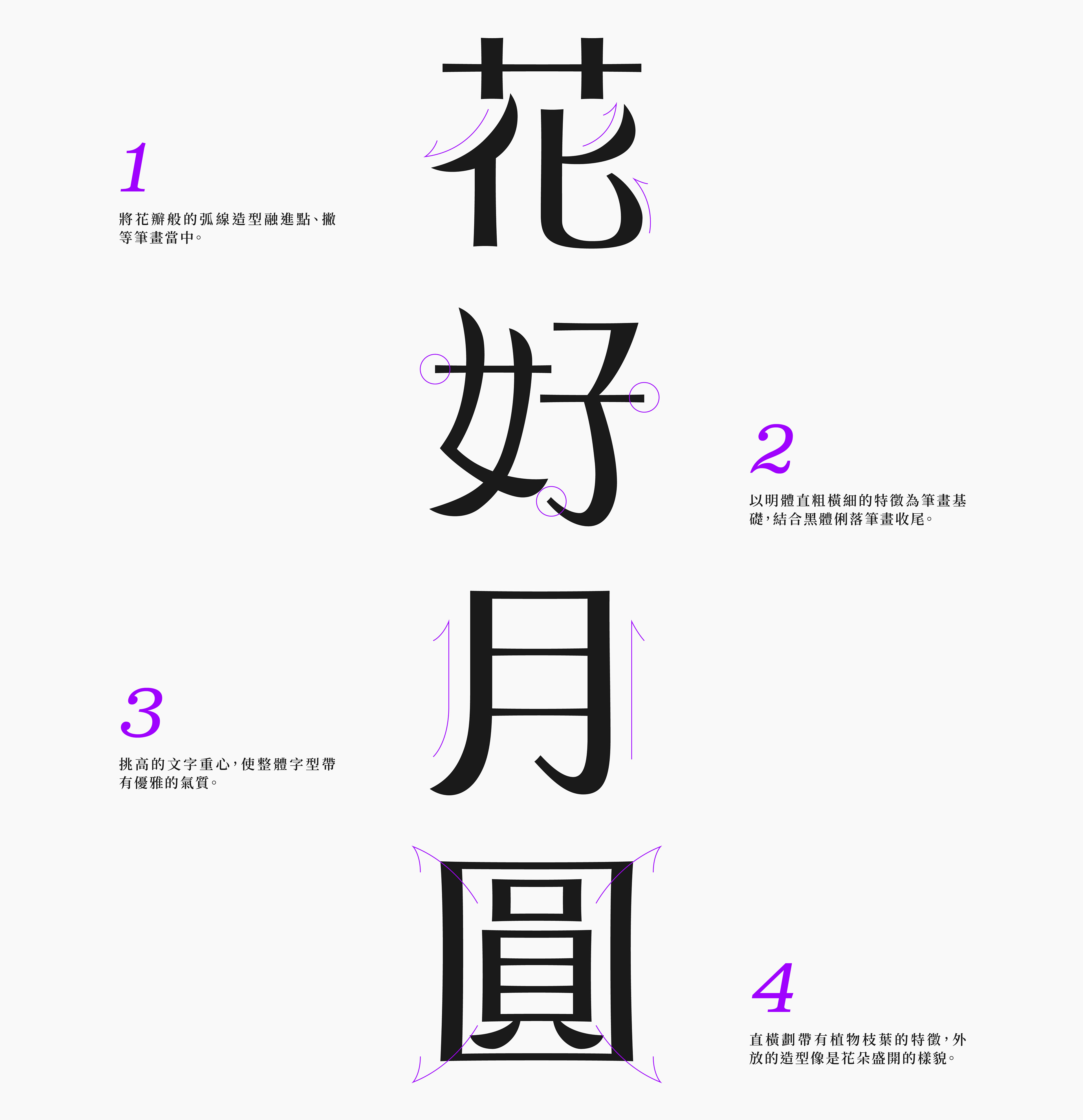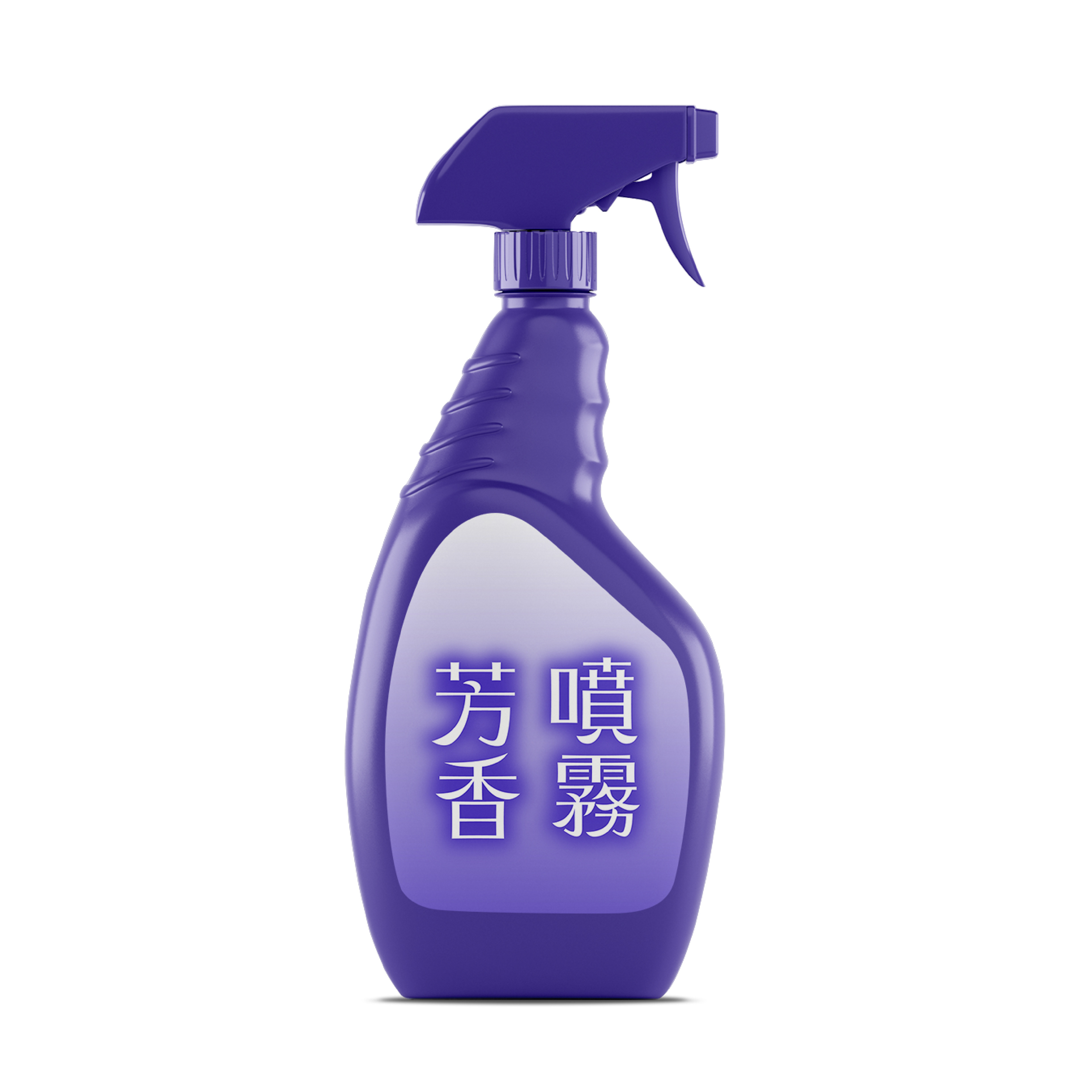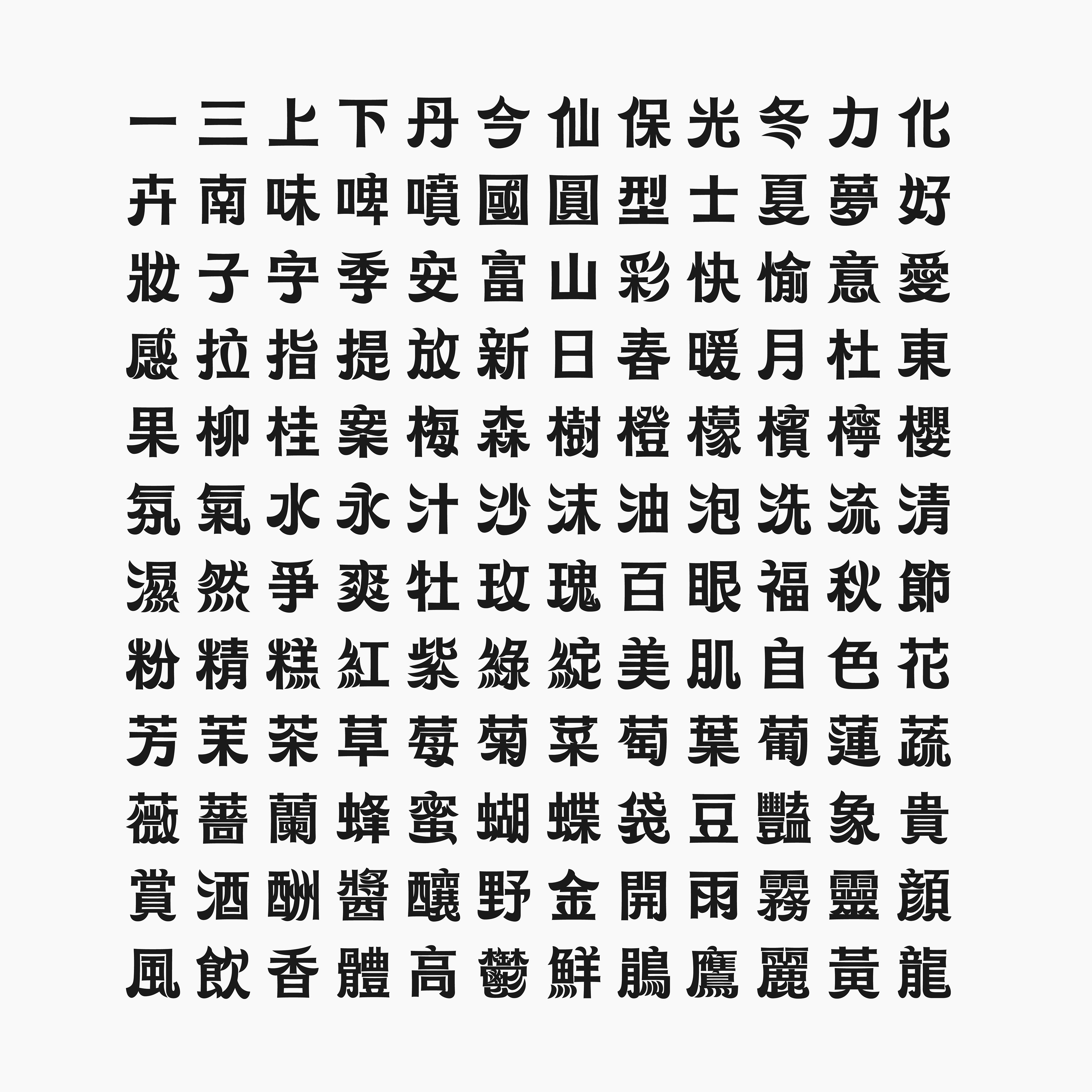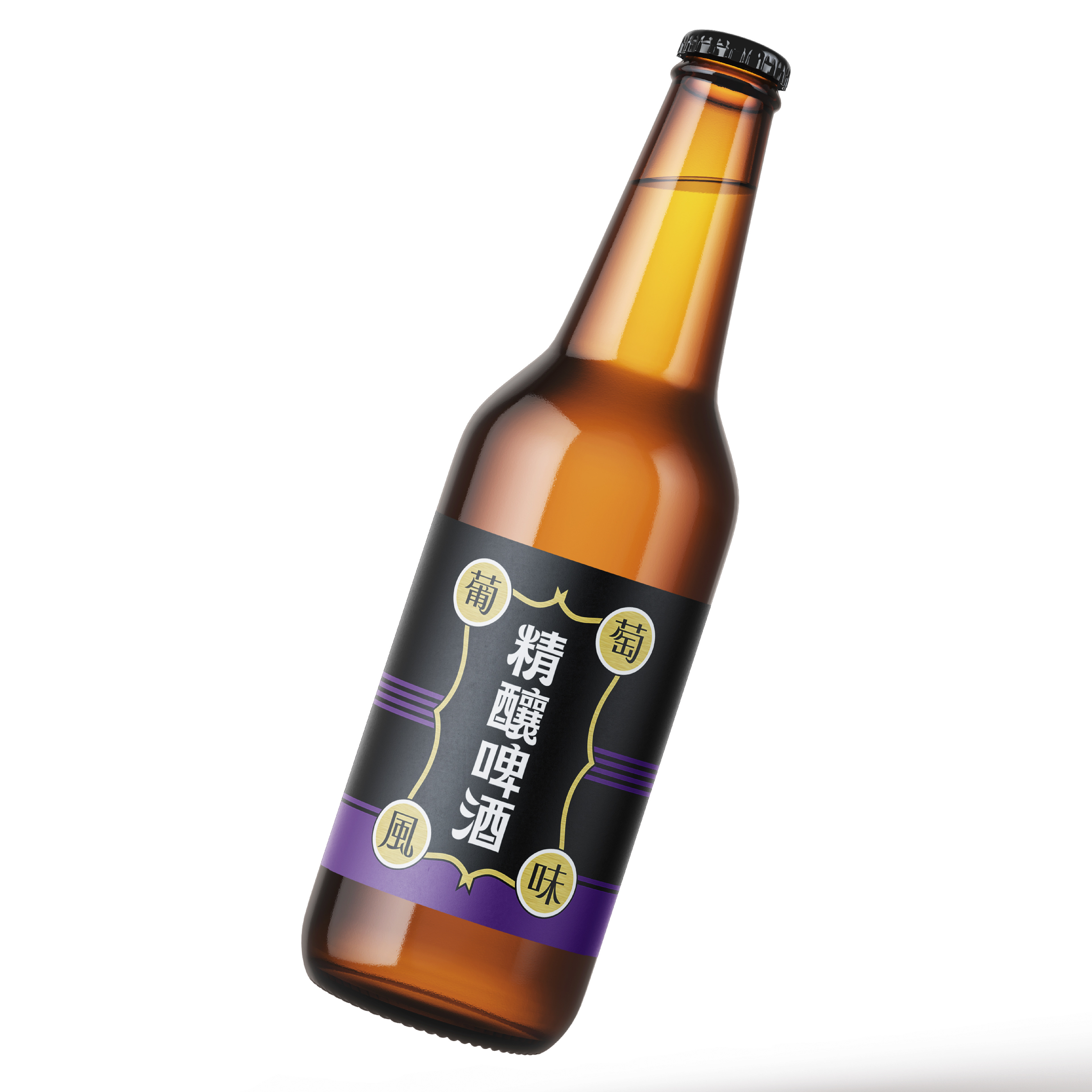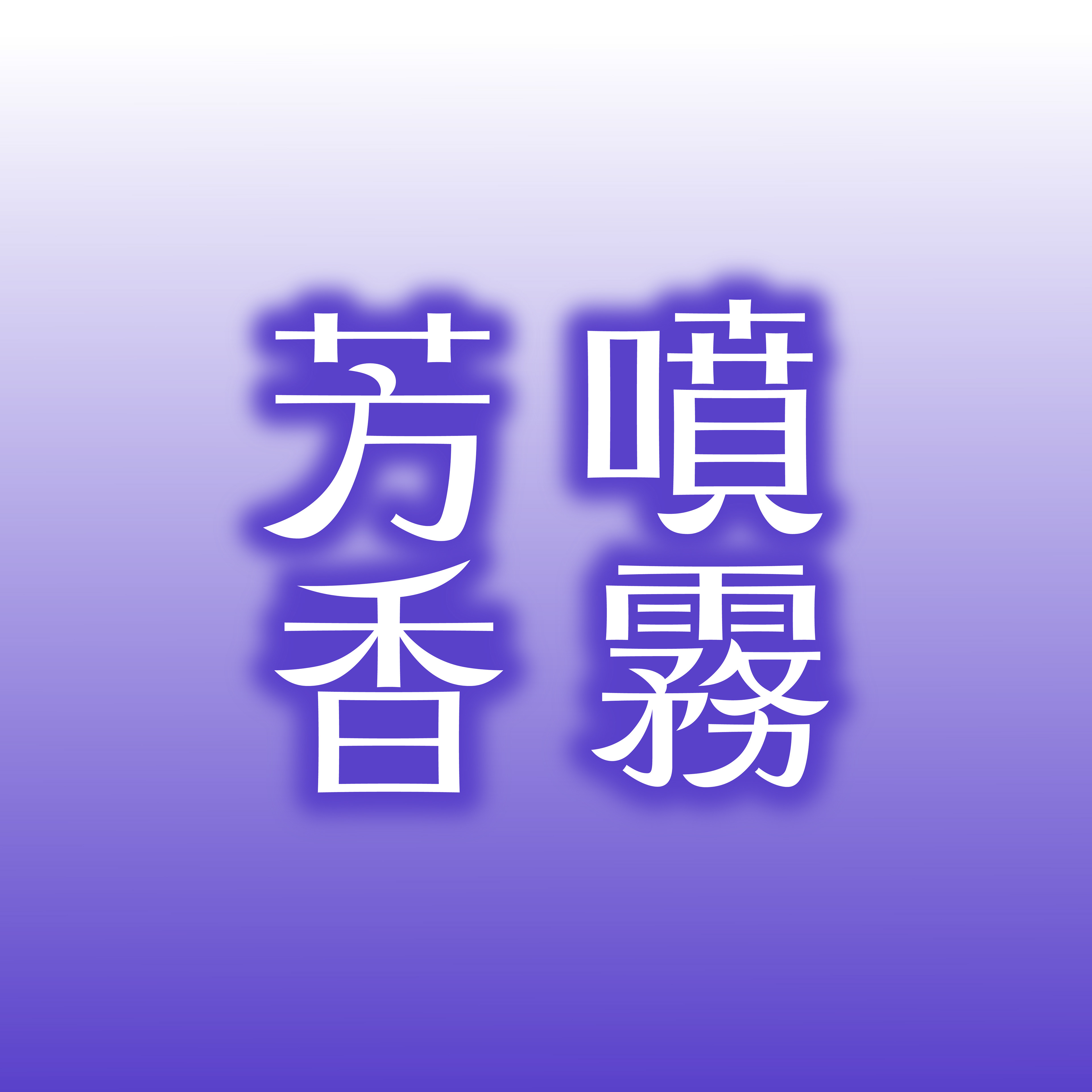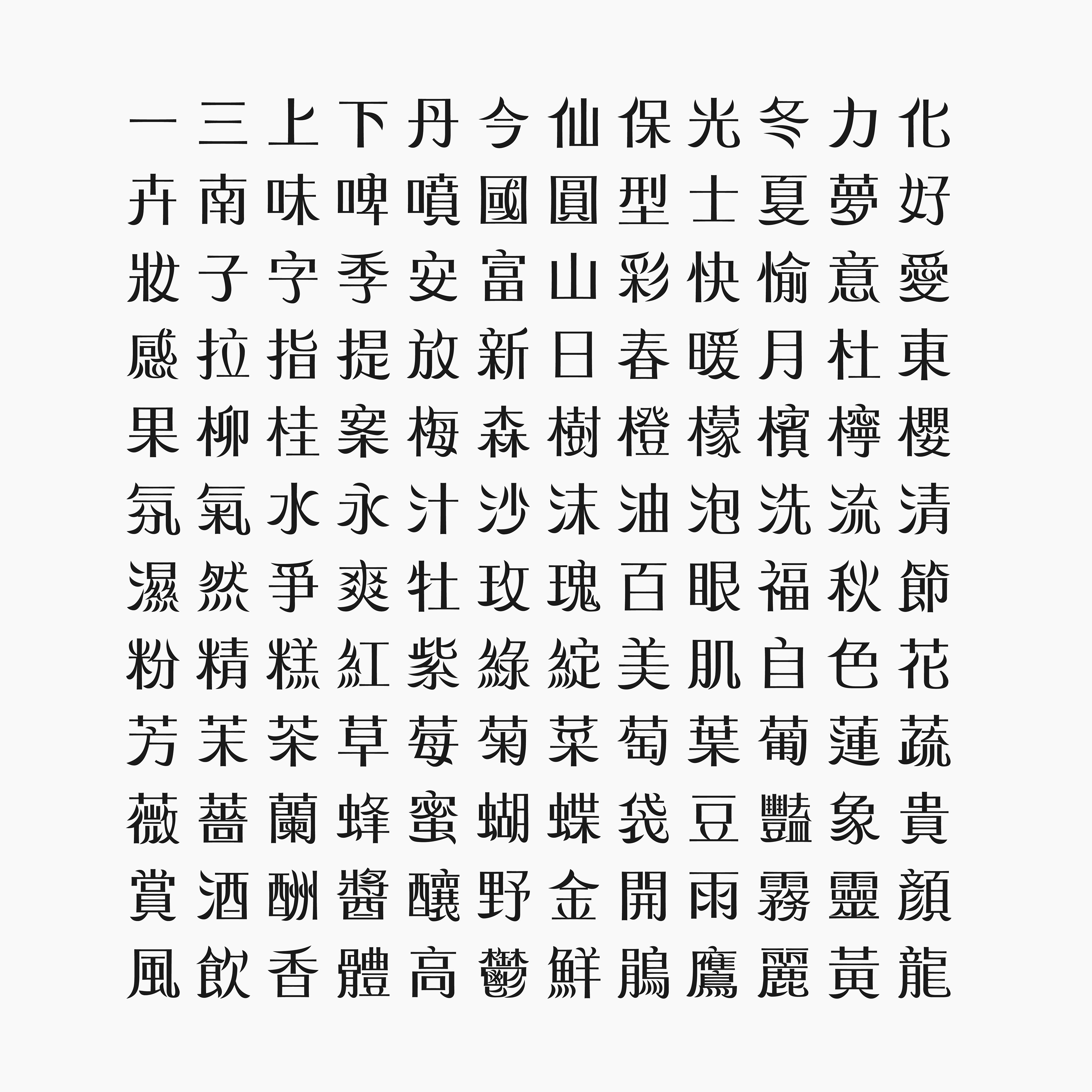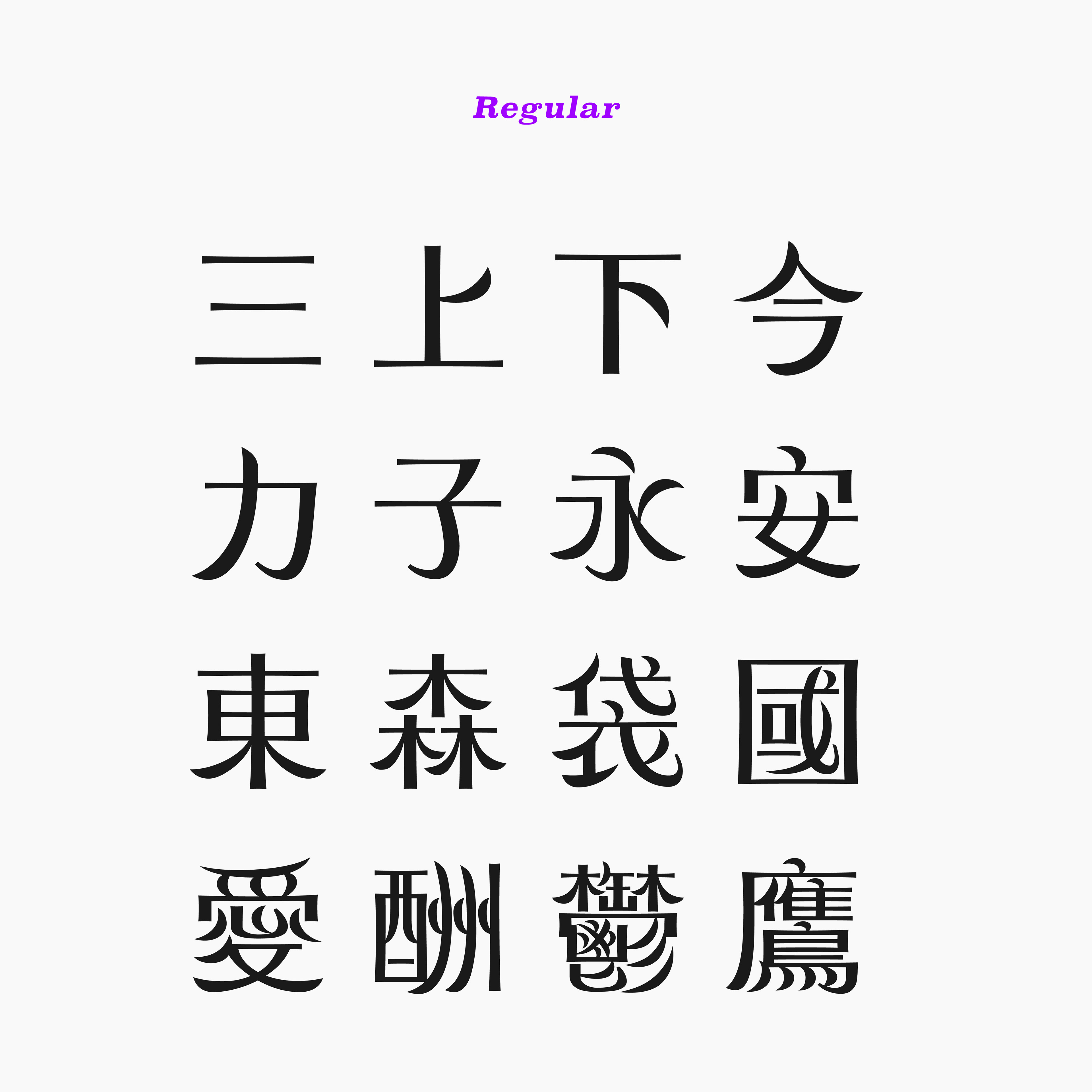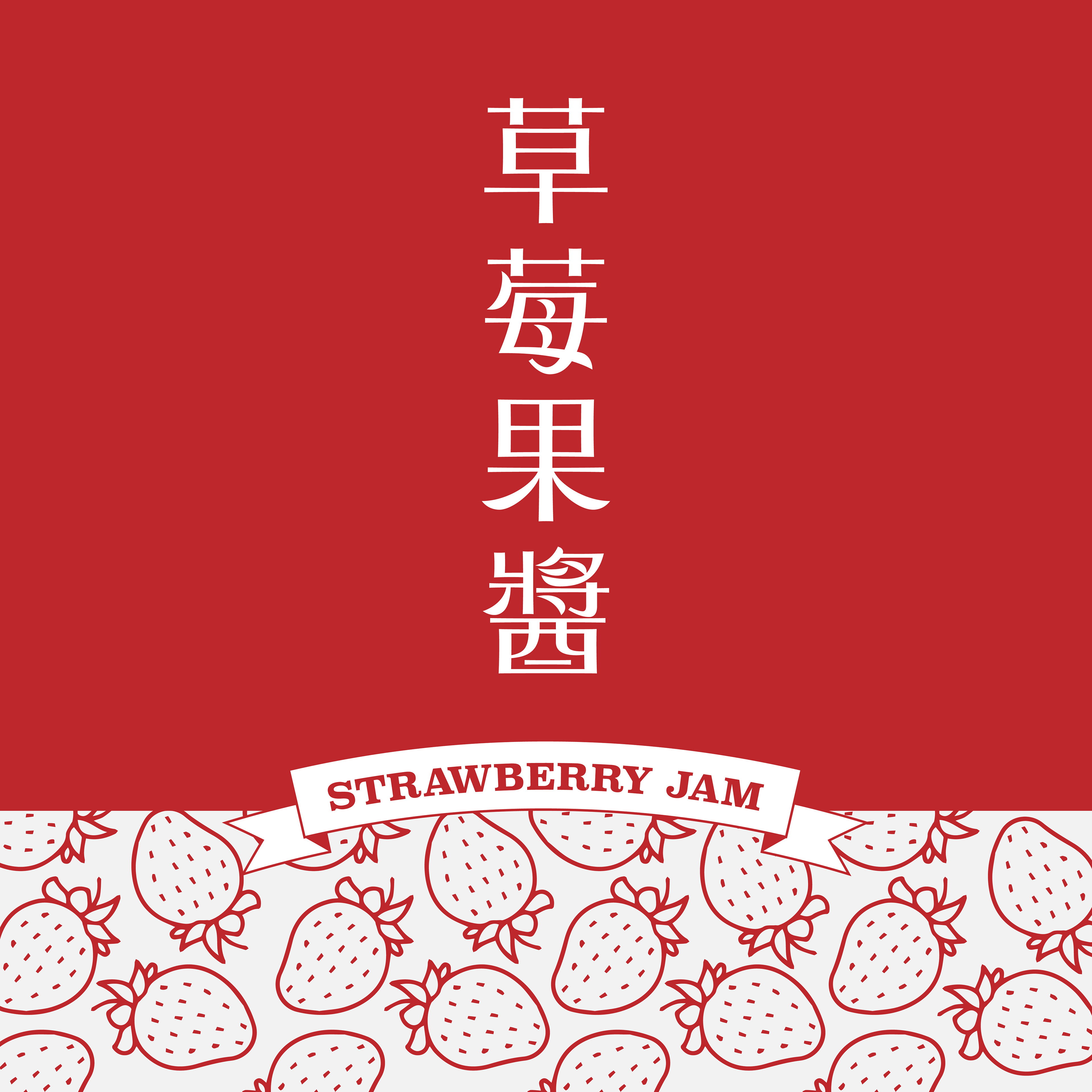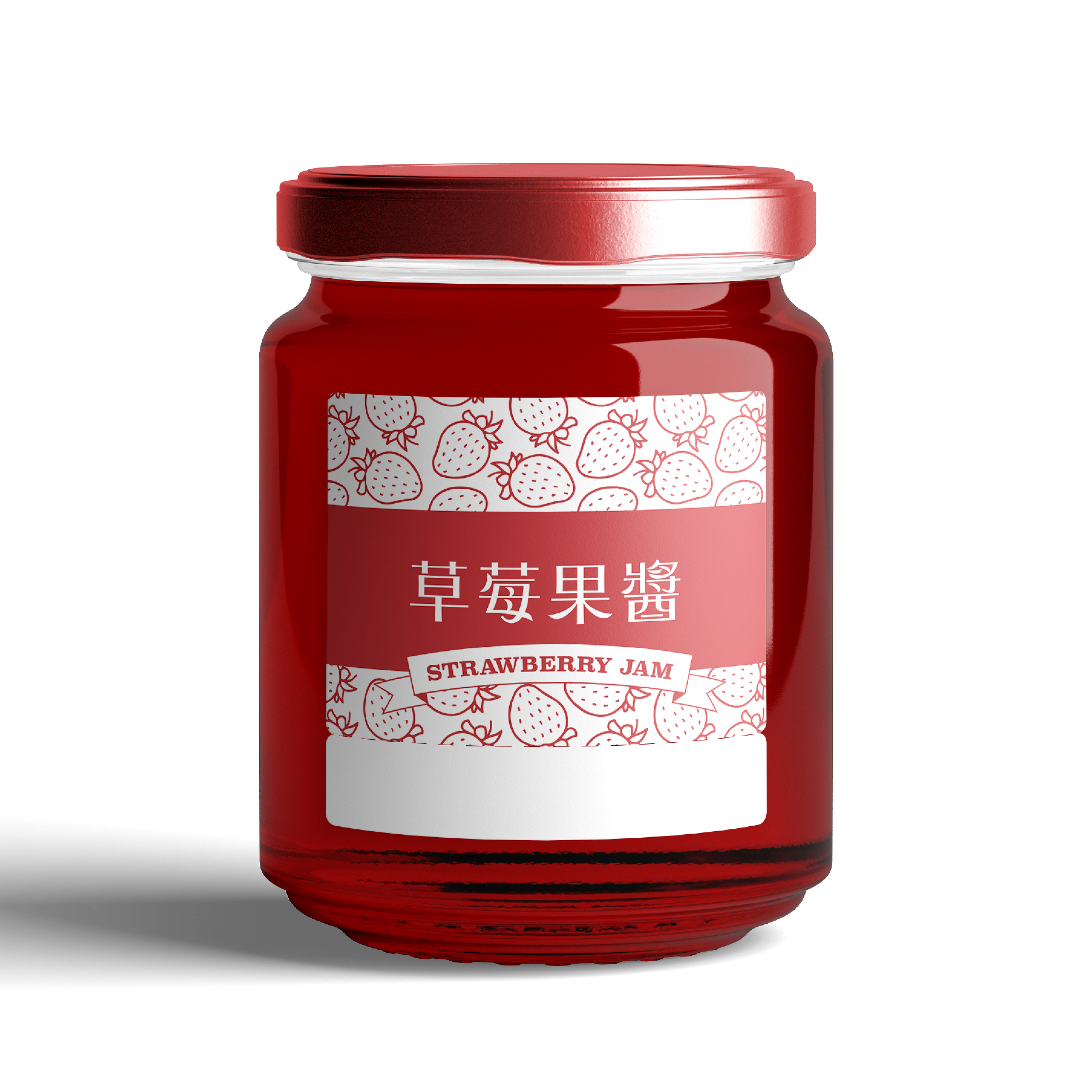
綻體 Blooming Font
以花卉造型為靈感,將花瓣圓弧的曲線融入筆畫之中,搭配可變式字型 (Variable Font) 技術的特性展現花朵綻放之意。字體以明體直粗橫細為基礎,結合黑體的俐落收尾,筆畫中段微內凹,營造盛放花朵般的放射效果,挑高的字重心增添優雅感。適用於食品包裝、節慶文宣、香氛與化妝品設計。
Inspired by floral forms, this typeface incorporates the gentle curves of petals into its strokes, utilizing Variable Font technology to convey the idea of blooming flowers. The typeface is based on the serif font style's thin horizontal and thick vertical strokes, combined with the clean, sharp finishes of sans-serif fonts. Slight inward curves in the middle of strokes create a radiating effect, reminiscent of flowers in full bloom. The elevated x-height adds a touch of elegance. This typeface is ideal for food packaging, festive promotions, fragrance, and cosmetic design.